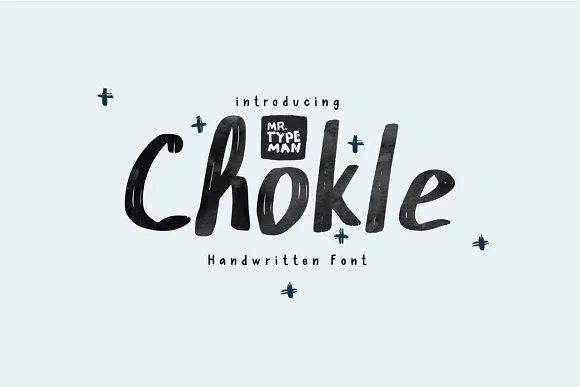
Descubra Chokle Font! Esta elegante tipografia funkiça foi criada por Mr.Typeman e está disponível gratuitamente na CreativeMarket. Chokle é perfeito para usar em logomarcas, cartões de visita, convites e design editorial. Com suas letras maiúsculas, minúsculas e pontuação padrão completas, você pode criar designs incríveis rapidamente. Este tipo suave, mas com um toque de charme, certamente vai tornar seu próximo projeto uma realidade. Tente Chokle agora para dar o toque final em seus projetos!